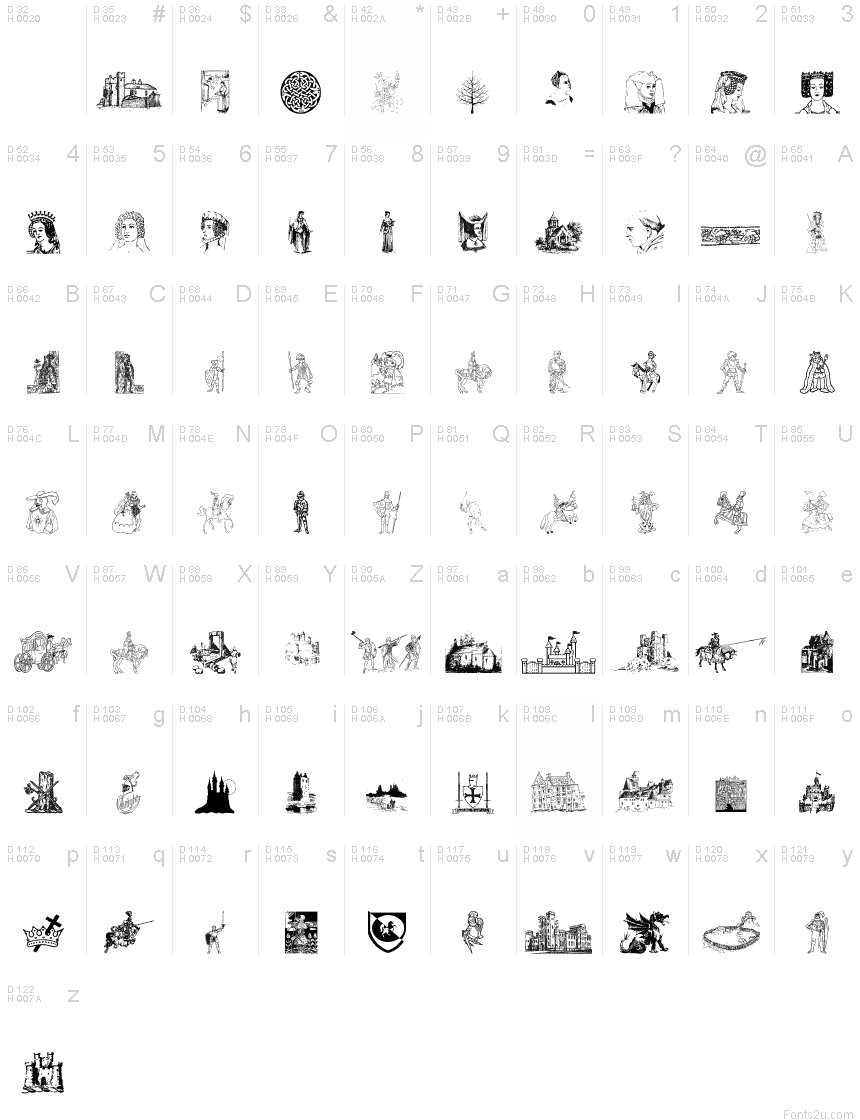
Die 001 Medieval Daze von Yellowyellow ist eine kostenlose Dingbat-Schrift im mittelalterlichen Stil. Sie besticht durch fein gezeichnete Porträts, Kleider und Burgsilhouetten, die an alte illuminierte Manuskripte erinnern. Die Linienführung ist detailliert und zugleich leicht rau, was jedem Zeichen einen handgezeichneten, zeitlosen Charakter verleiht und Ihre Layouts sofort in eine historische Stimmung versetzt.
Mit 001 Medieval Daze fügen Sie Fantasy-Buchcovern, Rollenspielmaterialien, Museumsplakaten, historischen Arbeitsblättern, Hochzeitspapeterie oder thematischen Websites im Handumdrehen erzählerische Elemente hinzu. Die Schrift kommt besonders groß zur Geltung, da jedes Symbol wie eine kleine Illustration wirkt. Kombinieren Sie sie für eine bessere Lesbarkeit mit einer schlichten Serif oder Sans Serif für den Begleittext.